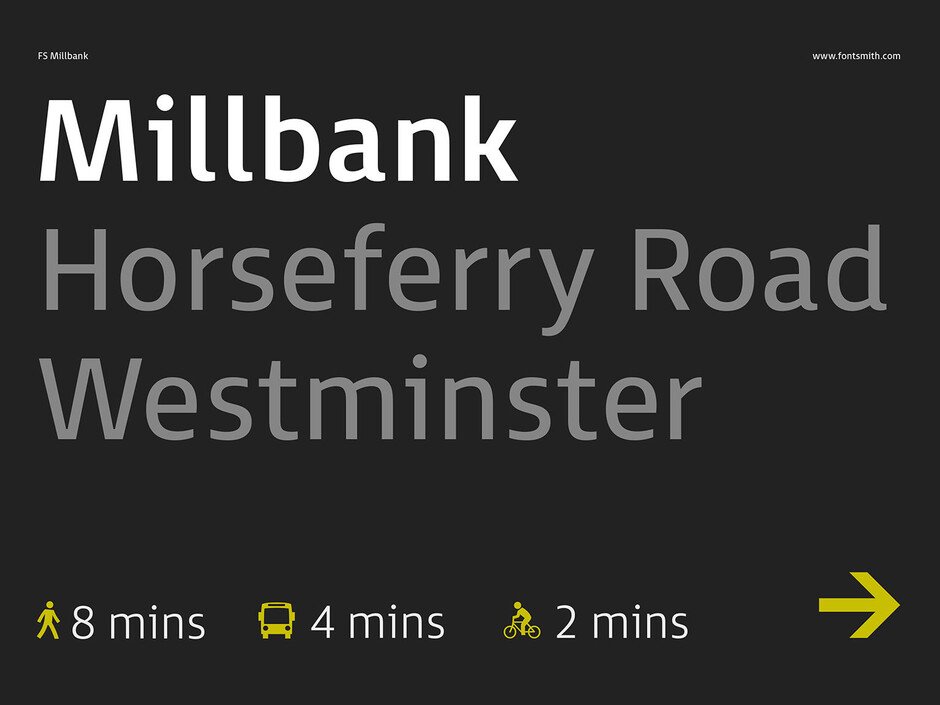
FS Millbank® - A quoi doit ressembler la typographie de l'orientation ?
Les caractères et la typographie font partie intégrante du monde moderne dans lequel nous vivons aujourd'hui. Aujourd'hui plus que jamais, nous sommes entourés de signes, d'icônes et d'informations visuelles qui nous disent d'aller ici, là ou quelque part. Pouvez-vous imaginer un monde sans direction graphique ou sans orientation visuelle ?Stuart de Rozario
Jason et Phil m'ont approché avec l'idée de créer une police de caractères pour la signalisation - quelque chose qui rivaliserait et remettrait en question les formes de signalisation Frutiger et Helvetica testées et éprouvées, presque omniprésentes, que nous voyons si souvent autour de nous aujourd'hui. Après avoir examiné la multitude de polices de caractères qui servent à la typographie de signalisation, j'ai effectué des recherches approfondies sur les critères très variés qui font la réussite d'une police de caractères de signalisation, et une partie essentielle de ces recherches a consisté à rencontrer les principaux concepteurs de signalisation de l'industrie pour connaître les exigences auxquelles ils sont confrontés lorsqu'ils sélectionnent les polices de caractères appropriées pour leurs projets. Les résultats de mes recherches m'ont également appris que dans ce monde technologique en constante évolution, nous exigeons beaucoup plus des polices de caractères et de la façon dont les formes de lettres et les mots réagissent aux différentes conditions de l'environnement - comme un mauvais éclairage, des perspectives de vue différentes et la tentative de déchiffrer des informations dans des espaces encombrés pendant les déplacements.Il fallait également tenir compte de l'aspect des caractères à l'écran en différentes tailles pour les appareils, les applications, les itinéraires et les affichages électroniques, ainsi qu'à l'impression. Un voyage ardu mais passionnant m'attendait. Grâce à l'analyse de caractères de signalisation largement utilisés sur différents tests de longueur de ligne, la façon dont ils diffèrent en proportion par rapport au chapeau à la hauteur x, l'espacement entre les caractères, les caractéristiques des glyphes, les combinaisons de lettres, le poids ou l'épaisseur des tiges et les proportions, les ouvertures et l'efficacité des empattements sur les lettres clés telles que "I", "i" et "l", toutes ces informations m'ont donné une étincelle d'inspiration pour concevoir quelque chose de nouveau.
J'ai utilisé ma méthode préférée pour dessiner avec un crayon et du papier, ce qui m'a permis de penser visuellement et de noter rapidement mes pensées et mes idées - les premières esquisses ont constitué un excellent point de départ. J'ai ensuite dessiné les lettres de base, plus précisément A, H, K, O, a, e, g, n et les chiffres 1, 2 et 3. Je savais dans quelle direction je voulais que la police de caractères aille. Quelque chose d'audacieux et de percutant, de solide et de robuste, mais d'humain et de plein de personnalité, de sans effort et de polyvalent, tout en espérant créer une police de caractères qui résistera à l'épreuve du temps et gardera sa fraîcheur dans les années à venir.
Dans le but de concevoir et de développer une police de caractères hautement lisible, fonctionnelle mais distinctive, la force motrice de mon processus de réflexion a été de m'assurer que la police était aussi claire que possible - je voulais éliminer tous les caractères ambigus possibles. La meilleure façon d'y parvenir était de tester la police dans une variété de tailles pour reproduire l'utilisation en petite taille, comme sur un totem d'information à partir de 6 pt jusqu'aux grands écrans numériques de départ à 900 pt. Lorsque les écrans lumineux sont en situation de rétroéclairage, les lettres et les mots semblent briller, se déformer et provoquer des halos (la diffusion de la lumière au-delà de ses limites propres provoque un effet de halo qui entoure les lettres, ce qui fait paraître la police plus lourde), j'ai créé des tests de flou à l'écran pour reproduire cet effet. Mes recherches ont également montré que les concepteurs d'outils d'orientation souhaitaient disposer de jeux de graisses positives et négatives. J'ai créé une gamme de graisses négatives afin d'obtenir un équilibre visuel correct entre l'utilisation de la FS Millbank sur une couleur claire ou foncée. Des tests positifs et négatifs utilisant la police dans différentes tailles de points à l'écran et sur papier ont été utilisés dans le cadre du processus de test global.
L'affichage des lettres floues et déformées m'a permis de me concentrer sur la structure squelettique de base des glyphes et de mettre l'accent sur certaines parties où les formes devenaient illisibles ou difficiles à déchiffrer, par exemple : un "a" à un seul niveau ressemble-t-il à un "o" ? de même, le "l" minuscule peut ressembler à un chiffre 1. L'espacement des lettres peut également se fragmenter et se confondre s'il n'est pas pris en compte de manière appropriée.
Cependant, aucune police de caractères ne peut être complète sans un ensemble d'icônes qui complètent la famille de caractères. La conception d'un jeu d'icônes pose ses propres problèmes : les icônes peuvent-elles tenir en petite taille ? Sont-elles immédiatement reconnaissables ? Ces questions sont primordiales lors de l'élaboration du jeu d'icônes. J'ai donc commencé par concevoir une grille circulaire complexe en utilisant les proportions de la police Cap et j'ai esquissé des icônes clés telles que les chiffres, les flèches, la voiture et l'avion afin d'évaluer le caractère général et la personnalité qui me semblaient appropriés. Le jeu d'icônes FS Millbank comprend 172 icônes couvrant un large éventail d'applications telles que les flèches, les transports, les informations générales et l'interface utilisateur, conçues pour aider les gens à se déplacer.
FS Millbank constitue la solution parfaite lorsqu'une clarté optimale est absolument essentielle. Le résultat global est une police de caractères d'une beauté qui lui est propre. Elle coule de manière exquise, est résolument humaine et déborde de personnalité. Mais fondamentalement, elle est tout à fait lisible et conçue de manière experte pour la clarté.